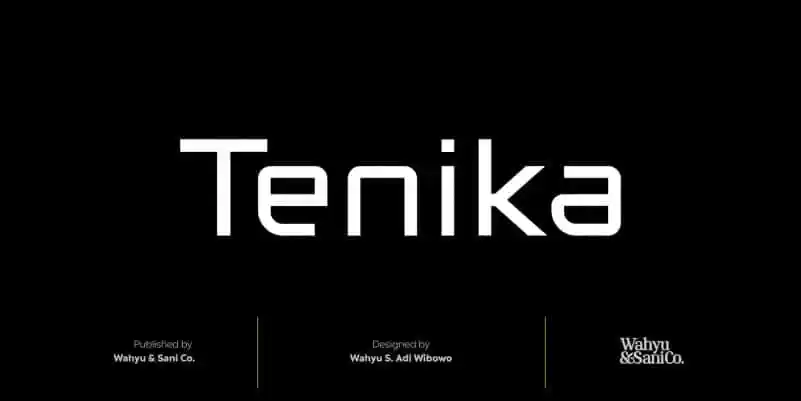
Tenika Sans Serif Font
A Tenika Sans Serif é uma fonte sans-serif que surgiu de forma acidental na criatividade inabalável dos designers Wahyu & Sani Co . Com formas angulares e um design limpo, essa fonte traz ao seu projeto um toque moderno e elegante. Ela foi desenvolvida a partir de uma modificação daquela que conhecemos como “quadro”, para atender especificamente às pequenas letras do alfabeto. A Tenika é também personalizada para incluir as grandes letras, possibilitando assim uma variedade de uso tanto em configurações retangulares quanto obliquas (ou itálicas). Com suporte aos caracteres da língua latina ocidental, que também incorpora alguns sinais fracionários e ligaturas. Obrigado a quem buscou novos recursos visuais para seus projetos digitais – é uma fonte ideal para qualquer projeto que valorize o estilo moderno e sofisticado. Também inclui arquivos Web Font (.woff) para garantir uma experiência de leitura fluida em diversos dispositivos.